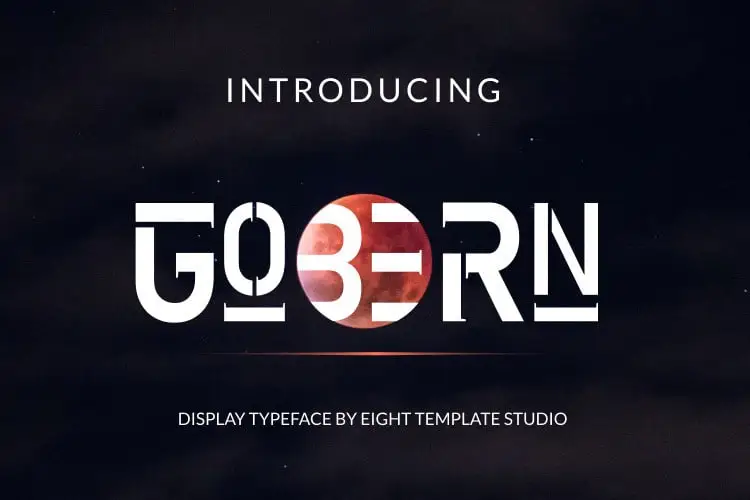
Gobern Display Font – Download Grátis
A Gobern Display Font é uma escolha inegável para quem busca destaque no seu design visual. Ela traz uma personalidade poderosa e autêntica, ideal para estilos de design que exaltam a força e simplicidade moderna. Seja ela usada em logotipos impactantes, headlines chamativas ou como elemento decorativo nas suas páginas web, a Gobern Display garantirá que sua mensagem seja notada. Se você está procurando por uma fonte que combine elegância com confiança, essa é sua fonte perfeita. Ela não apenas adicionará profundidade e interesse visual ao seu design, mas também destacará seus ideais criativos. Esta fonte de display oferece uma versão poderosa para quem busca destaque na web ou em qualquer projeto gráfico que exija um estilo forte e confiante.